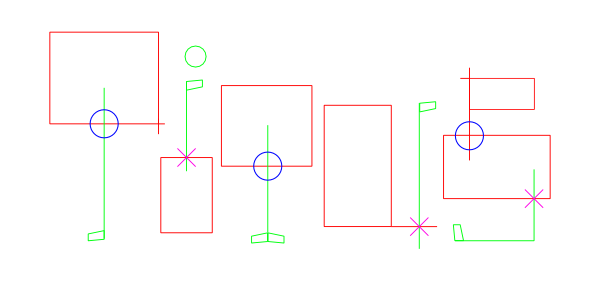
Brauche Hilfe beim Kolorieren einer Arbeit
Ich bastele gerade etwas, für einen kleinen Design-Wettbewerb von Titus-Skateboarding, habe aber leider große Probleme, vernünftige - cool, stylisch und edel sollen sie sein - Farben zu wählen. Da ich aber unbedingt bei diesem Wettbewerb zumindest so sehr auffallen möchte, dass ich mal für ein reguläres Design von Titus Typo machen darf, brauche ich ganz dringend eine Farb-Vision, die sich bislang so gar nicht einstellen will.
Das hier ist die grob gekernte schematische Darstellung für unters Transparentpapier:
Was nachher ungefähr so aussieht. (Dann sieht auch das "S" nicht aus wie ein Segelboot mit Gendefekt...):
- Das Ganze soll auf einem schlichten weißen Hintergrund/Skateboard-Brett gedruckt werden. (Nix außer Schriftzug, nur am Rand ein kleines Icon von Titus.)
- Grün, Rot, Blau, Magenta-Teile sind jeweils eine Lage Transparentpapier, können also auch nach dem Scan leicht eine eigene Farbe zugewiesen bekommen.
- Die rot umrandeten Flächen könn(t)en mehrere Farbsegmente beherbergen, es sollte aber auch Weiß innerhalb der roten Umrandung erhalten bleiben, weil es stylisher aussieht.
- Jedes Kreissegment _kann_ _eine_ Farbe beherbergen. Grün umrandete auch.
Da ich mich nicht mal ansatzweise für Farben entscheiden kann, brauche ich wirklich dringend Inspiration. Links zu Unternehmen/Designs mit ähnlichen Buchstaben, um mir anzugucken, wie man so was kolorieren könnte, wären gerade allerdings schon sehr viel, weil ich echter Farb-Legastheniker bin. Rat von mitfühlenden Farb-Genies nehme ich aber auch gerne an. (Wobei die Farbkombinationen ruhig tausendfach dagewesen sein dürfen, sie müssen nur stimmig sein.)
Du willst an einem Wettbewerb mitmachen, um später regulär für Titus zu arbeiten und brauchst auf den ersten drei Metern schon Hilfe? Denkst du wirklich, dass du eine große Hilfe für Titus sein kannst? Nichts für ungut, aber das hört sich nach Kokolores an. :oops:
Ich bastele gerade etwas …
Sorry dass du hier deiner Illusionen verlustig gehst, aber der Eindruck "basteln" drängt sich mir auch auf. Mit Design hat das nichts zu tun. So überhaupt gar nichts.
Da ich aber unbedingt ... mal für ein reguläres Design von Titus Typo ...
Du willst an einem Wettbewerb mitmachen, um später regulär für Titus zu arbeiten und brauchst auf den ersten drei Metern schon Hilfe? Denkst du wirklich, dass du eine große Hilfe für Titus sein kannst?
… Euer Gelaber …
Das liest sich mehr unsocialized als ungermanized.
Wie bereits gesagt: Wenn das das ist, was Du da raus lesen magst, ist das so.
Andererseits habt ihr mir trotzdem geholfen. Ich fühle mich nämlich höchst herausgefordert.
Richtig so, Ungedeutscht! wird eh langsam mal wieder Zeit für 'nen internen Wettbewerb hier, was Mädels?
Bin ich der einzige hier, der diese schematische Darstellung überhaupt nicht kapiert? :cry:
was ich nicht verstehe:
Du willst an einem Wettbewerb mitmachen, um später regulär für Titus zu arbeiten und brauchst auf den ersten drei Metern schon Hilfe? Denkst du wirklich, dass du eine große Hilfe für Titus sein kannst? Nichts für ungut, aber das hört sich nach Kokolores an. :oops:
Sorry dass du hier deiner Illusionen verlustig gehst, aber der Eindruck "basteln" drängt sich mir auch auf. Mit Design hat das nichts zu tun. So überhaupt gar nichts.
hier im forum tauchen dauernd leute auf, die keine ahnung haben, welche schrift sie wählen sollen, obwohl sie beruflich damit zu tun haben und ihre entwürfe am ende sogar verkaufen wollen. die bekommen freundlich hilfe, auch wenn es »auf den ersten drei metern« ist. nun fragt jemand nach der farbwahl für einen wettbewerbsbeitrag und erntet nur spott bzw. belehrungen, wenn er anmerkt, dass das, was ich oben zitiert habe, keine hilfe ist. hat das irgendeinen sinn, so zu antworten, den ich nicht sehe? oder ist das ganze thema kokolores?
Ich glaube dass dieser desillusionierende Hinweis gegeben werden dürfen muss, um die potentielle Enttäuschung nicht zu groß werden zu lassen.